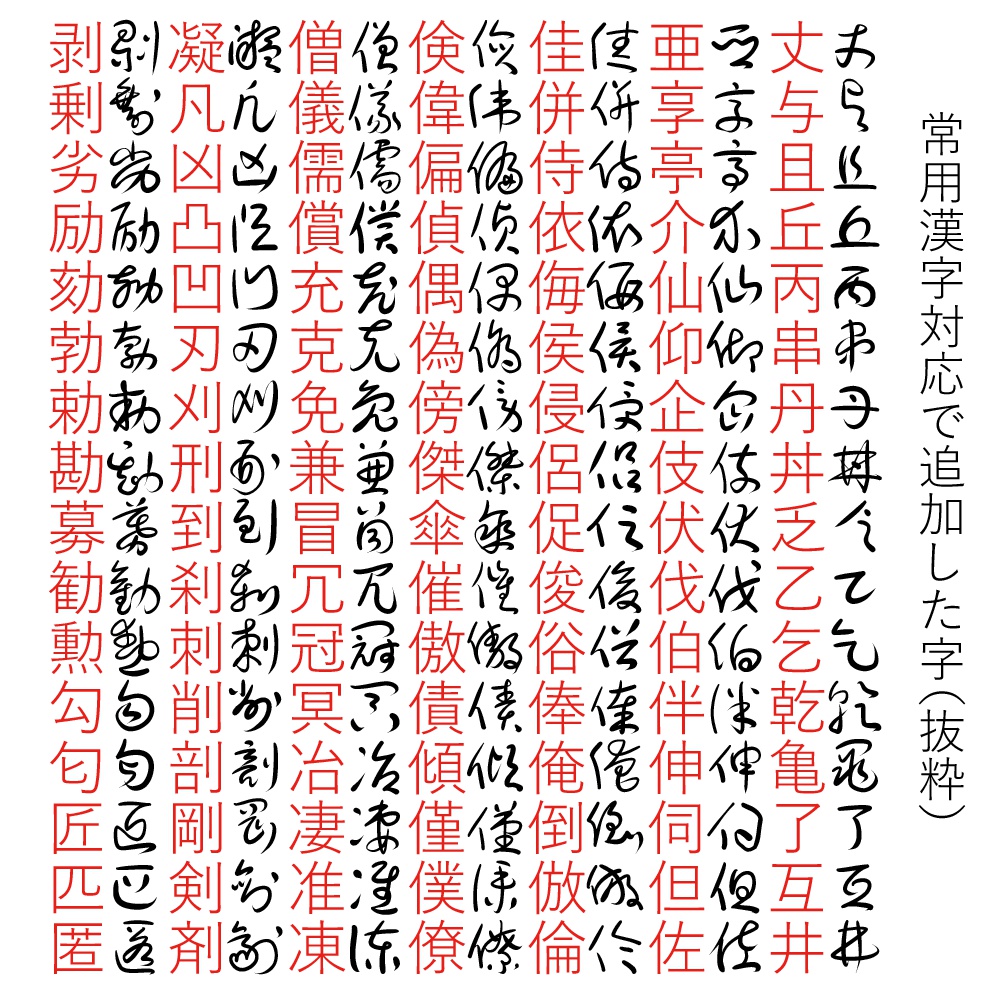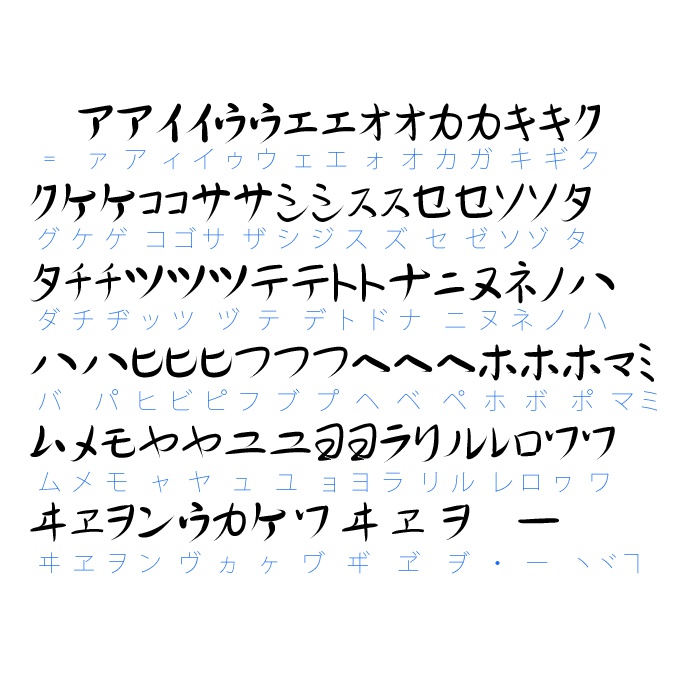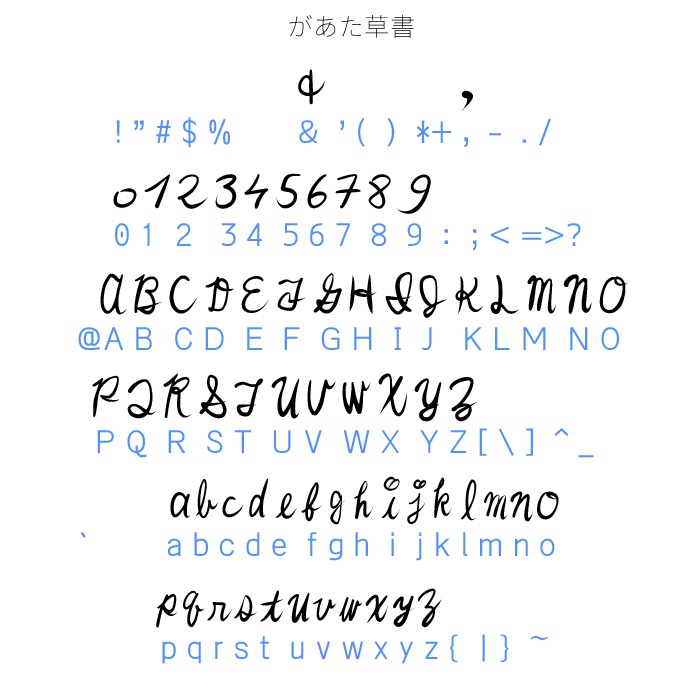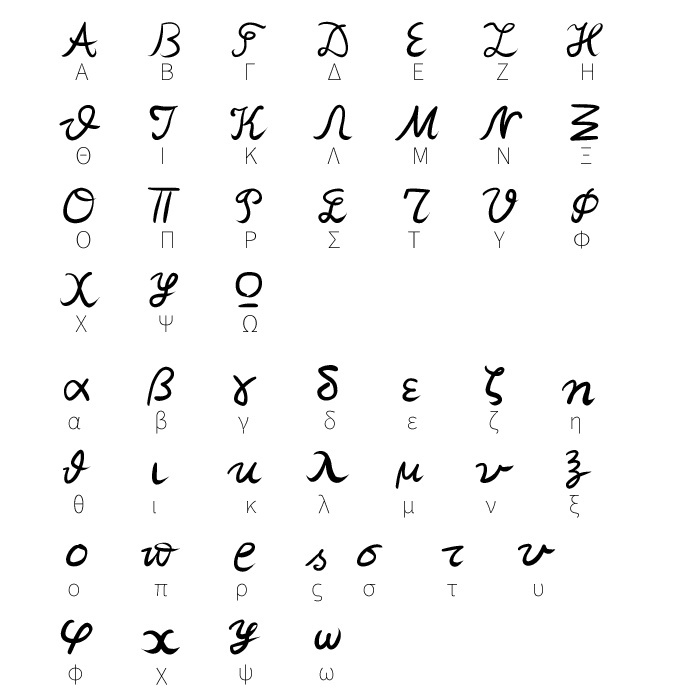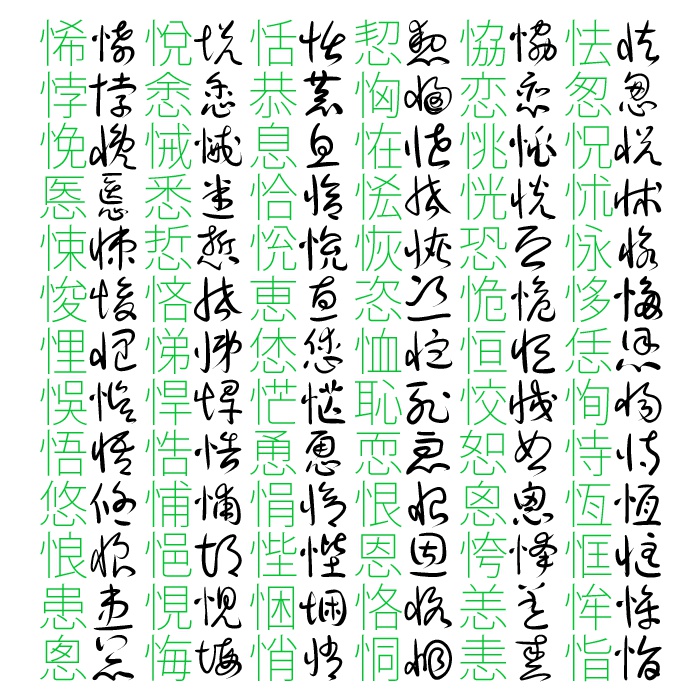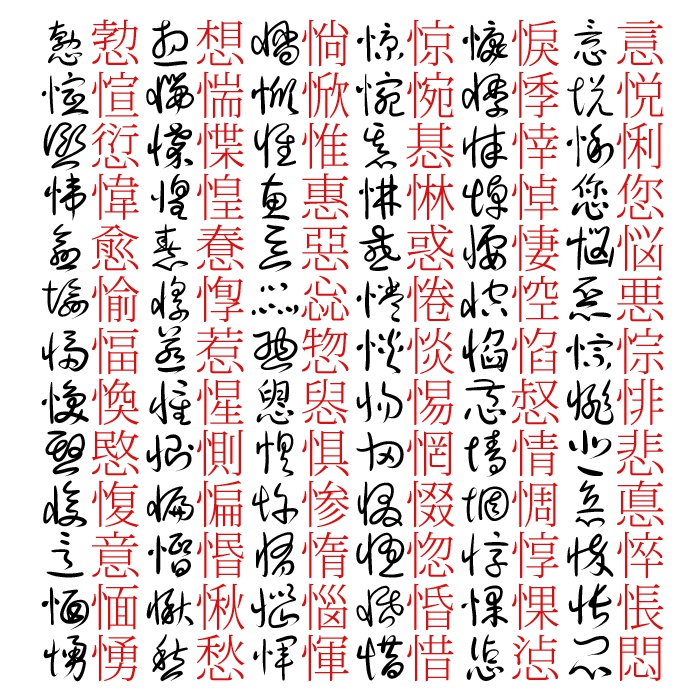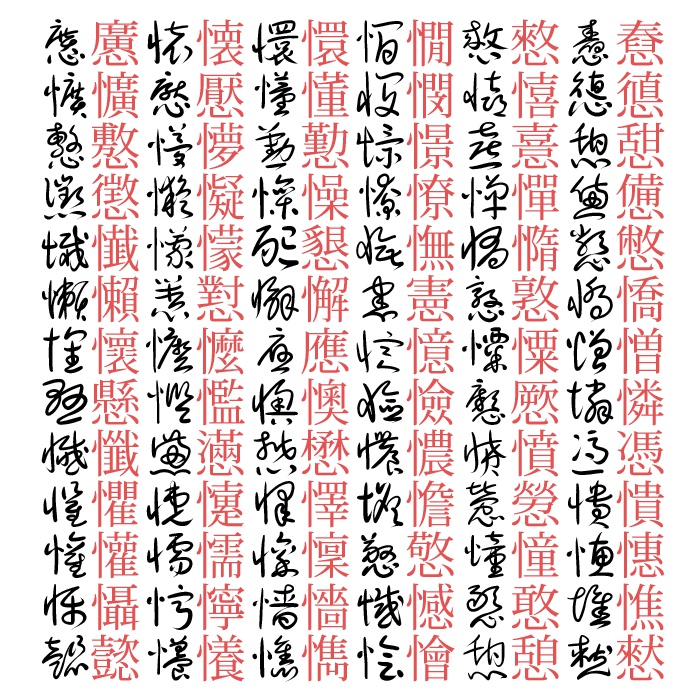
草書フォント(があた草書)
常用漢字対応しました! 平仮名が一部変体仮名になってます。普通の平仮名が良い場合は通常かな版(https://nukosuki.booth.pm/items/583797)をご使用ください。 草書、崩し字、筆記体のフォント。プロポーショナルです。 作者:があた。 類推により作字した草書体を含みます。 このフォントは商用問わず自由に使用・改造・再配布できますが全て無保証とします。 参考:書体小字典、くずし字用例辞典、衡山毛筆フォント草書、字源、ウィキペディア、新書道字典、google、フランスの数字の筆記体、筆記体フォントの数字、書法字典 収録:基本ラテン・ギリシャ文字・キリル文字・ひらがな・カタカナ・全角英数の一部又は大部分、CJK統合漢字のU4e00~668cの一部及びそれ以降の一部, 教育漢字(1989)1006字、常用漢字